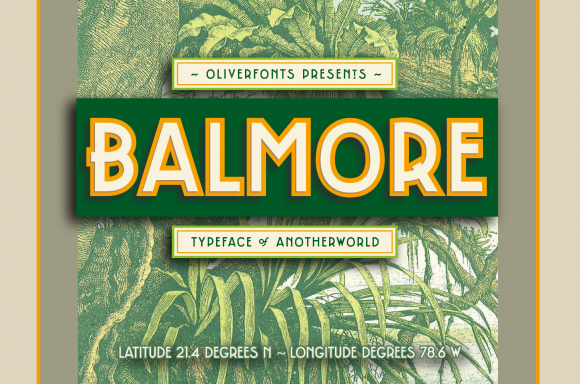
Balmore
Balmore: A Fonte Sans Serif que Une Art Deco e Modernismo
Se você está à procura de uma fonte all‑caps com personalidade, Balmore chega como a solução perfeita. Com linhas limpas, design minimalista e um toque inconfundível de Art Deco, ela traz ao seu projeto uma combinação rara de autenticidade vintage e originalidade contemporânea.
- Design clean e sofisticado – Balmore oferece um estilo sans serif equilibrado, ideal para quem deseja elegância sem excessos.
- Inspiração Art Deco – Cada caractere carrega os detalhes geométricos típicos da década de 1920, conferindo um ar de luxo retro ao seu layout.
- Versatilidade moderna – Apesar da forte pegada histórica, a fonte se adapta perfeitamente a projetos digitais, branding, embalagens e identidade visual.
- Uso exclusivo em caixa alta – Balmore foi criada para textos em
ALL CAPS, garantindo impacto visual imediato em headlines, logotipos e slogans. - Leveza e legibilidade – O espaçamento bem calculado e as formas simples tornam a leitura fluida, mesmo em tamanhos menores.
Ao escolher Balmore, você adiciona ao seu trabalho autenticidade e originalidade inesperada. Seja para uma campanha publicitária, um site de moda ou um convite elegante, esta fonte eleva a comunicação visual a um novo patamar.